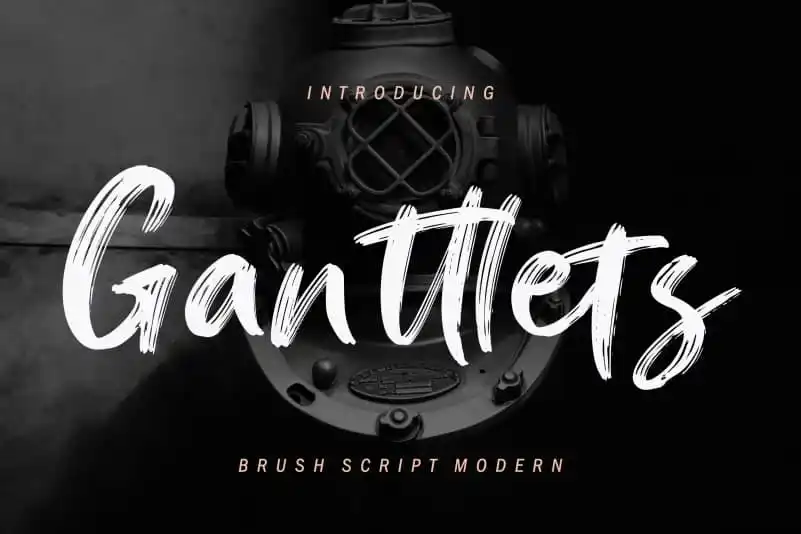
Presentamos com orgulho Ganttlets Brush Font, uma fonte tipo-têxtil feita à mão, perfeita para quem deseja dar uma sensação autêntica e artesanal às suas criações gráficas. Esta fonte é um verdadeiro mimo para designers em busca de estilos modernos e elegantes. Suave como o toque de um artista na tinta, Ganttlets Brush adquire a textura quase inatacável da arte feita à mão e proporciona uma sensação de autenticidade que se alinha perfeitamente com os projetos mais variados. Seja ela a base de seu próximo logotipo ou o motor do texto em sua nova página web, Ganttlets Brush promete adicionar um toque único e moderno ao seu trabalho. Com seu design leve e fluido, esta fonte script é perfeita para aqueles que buscam uma transição suave entre o digital e a arte autêntica. O resultado será sempre original e impecavelmente elegante, garantindo que suas criações sejam notadas de forma única e impactante no mundo da design visual. Além disso, seu estilo único faz dele um ótimo complemento para projetos tanto digitais quanto impressos, dando aos seus designs o toque sofisticado e autêntico que você sempre desejou. Ganttlets Brush é uma excelente escolha para quem busca uma fonte à mão que se destaca com facilidade, seja no campo da ilustração digital ou do design gráfico tradicional.